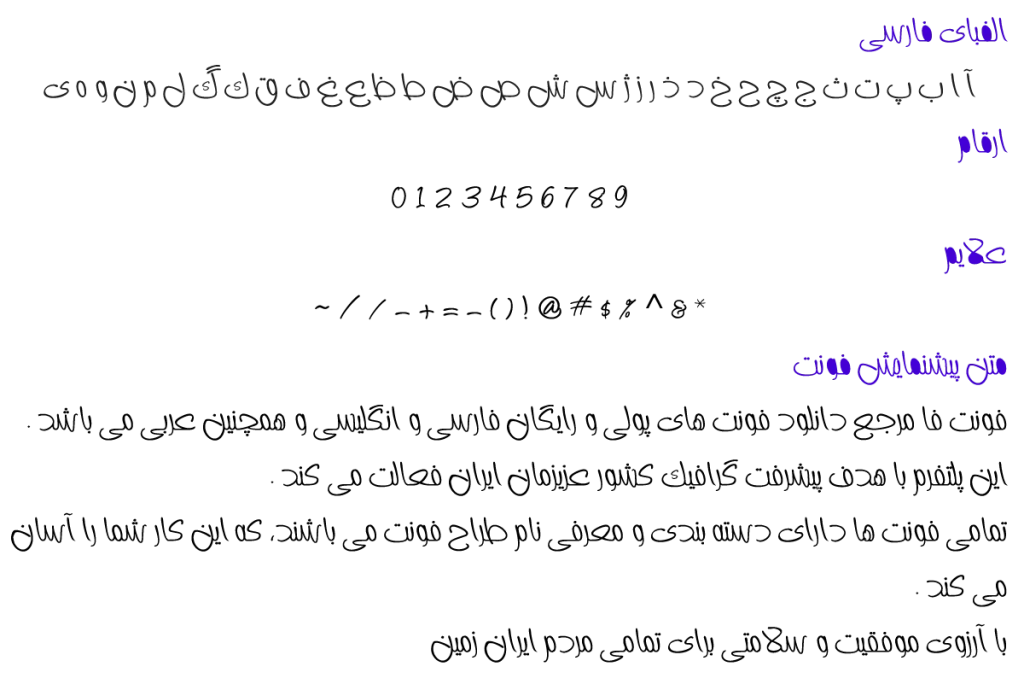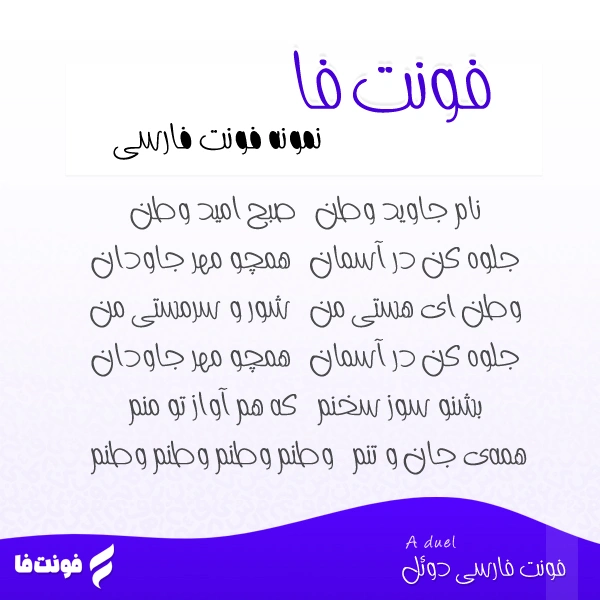
فونت فارسی دوئل – A Duel
طراح فونت: علی سواری نوع فونت: فونت فانتزی
پیشنمایش فونت دوئل
توضیحات و معرفی فونت دوئل
فونت فارسی دوئل ( A Duel ) از مجموعه فونت های آزاد می باشد، و نیز نوع فونت فانتزی می باشد.
فونت خوشگل مربوط توسط علی سواری در سال 1390 طراحی و ساخته شده است.
و نیز فونت A Duel در 2 وزن معمولی و فت است.
- A Duel Regular
- A Duel Fat
تصویر زیر، نمایی از این تایپ فیس را در قالب شعر «وطن» نشان میدهد.